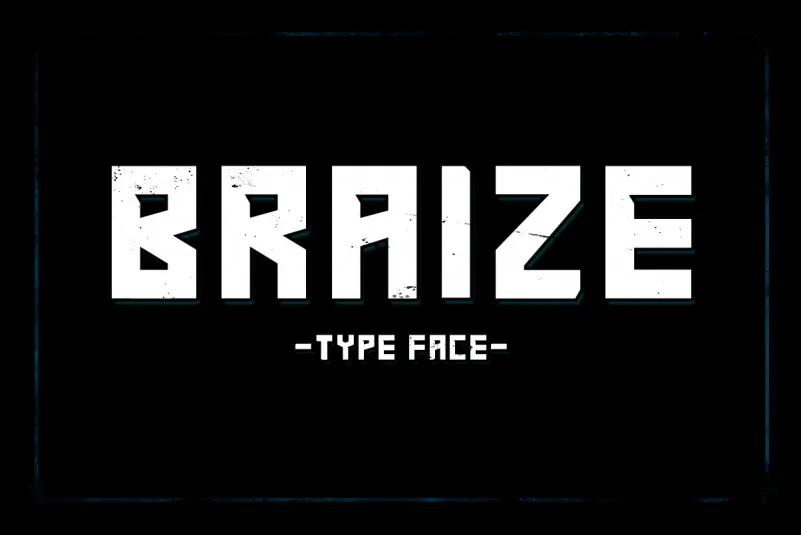
Braize Typeface – Download Grátis
Braize é uma fonte retro que captura a essência dos anos 80 e 90 com sua forma retangular levemente apertada, inspirada em letras estilizadas para roupas de futebol, anúncios grandes em placares, nomes de bandas e capas de livros. Suas linhas finas e robustez definem ela como uma fonte ótima para embalagens de produtos ou qualquer outra ocasião onde um visual alegre e moderno é desejado. Ideal tanto para criar designs pessoais quanto para profissionais que precisam de uma fonte versátil, Braize oferece um toque nostálgico e elegante sem sacrificar funcionalidade. Suas letras estilizadas trazem à tona o espírito retro da sua marca, tornando essa fonte ideal para diferentes tipos de projetos gráficos.